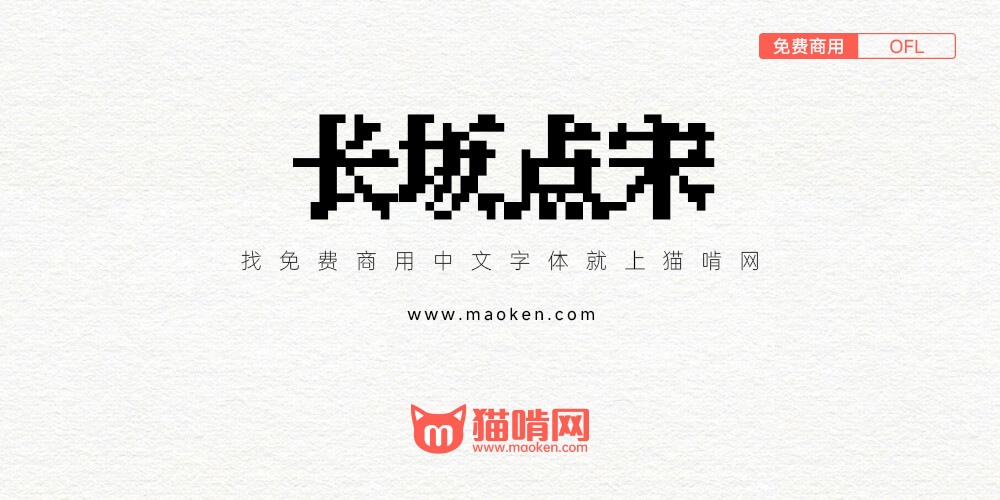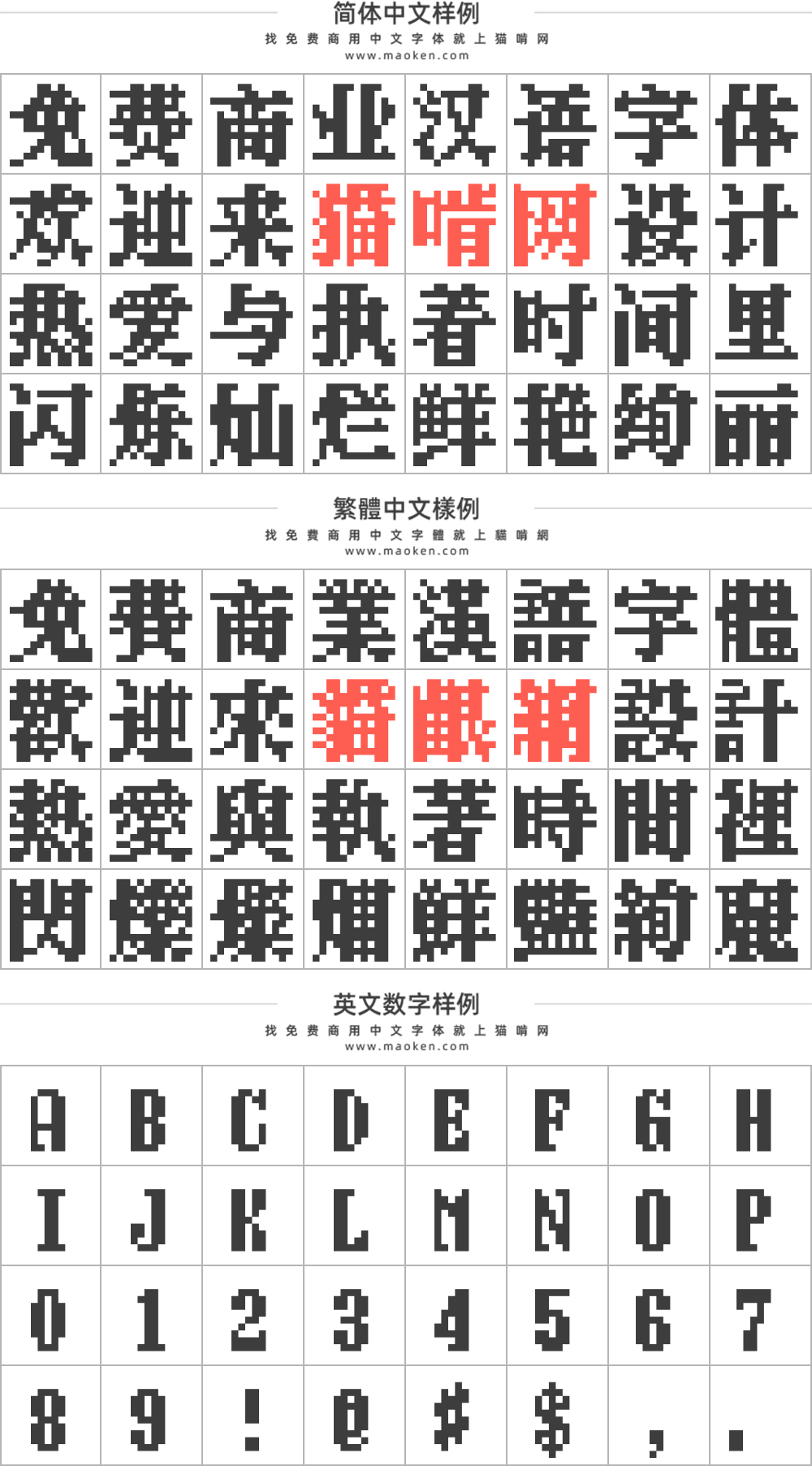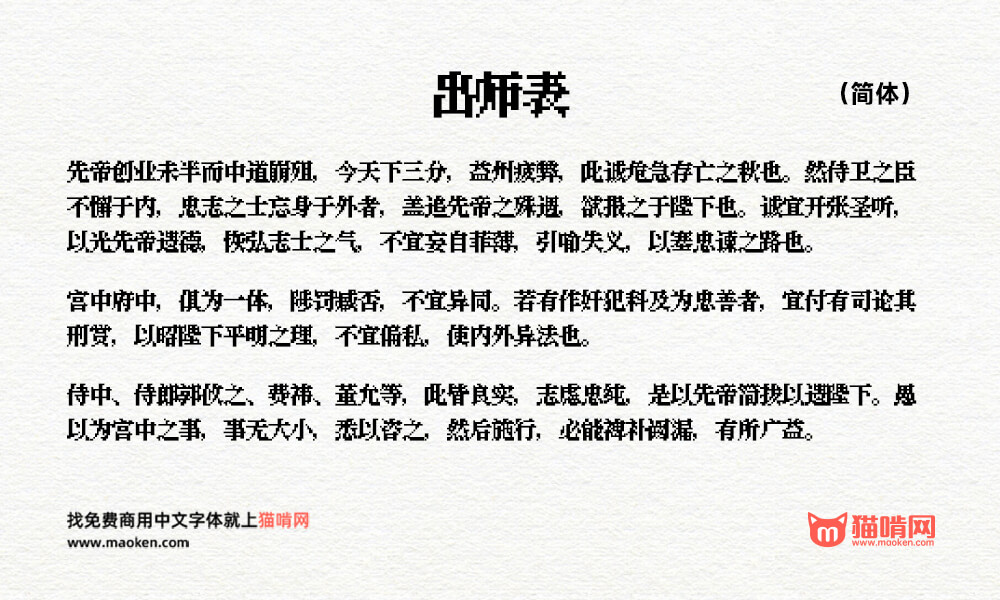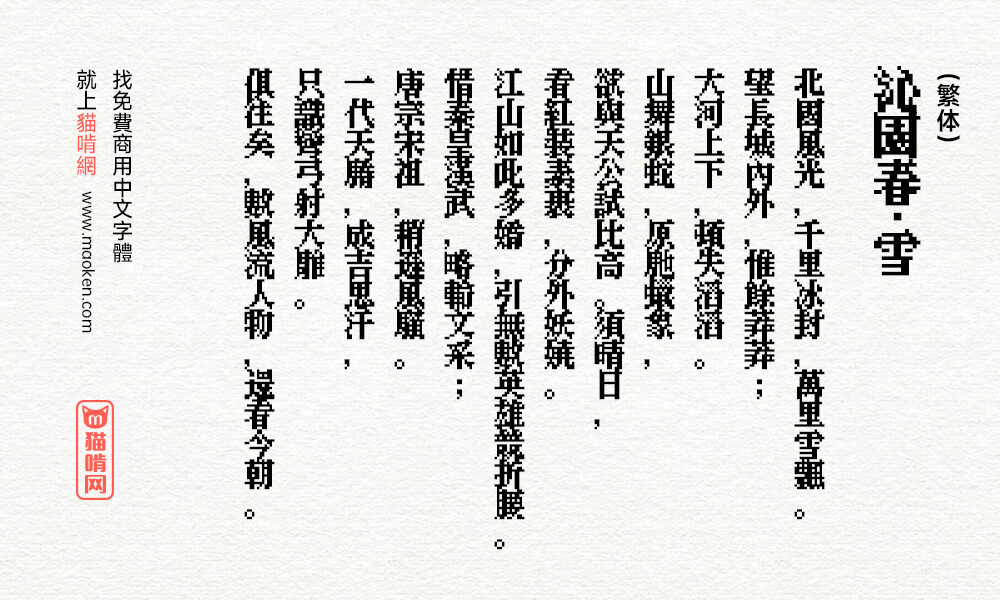
「长坂点宋 12」是基于 「KHドットフォントシリーズ」中的「KHドット道玄坂12」补足简体字和部分繁体字的 12px 点阵粗宋体,适合在复古风格的游戏和招牌中使用。
补全GB2312字符集中的所有汉字与部分常用繁体字,并调整部分汉字字形;补全汉语拼音与注音符号。
此外,部分竖画较多的汉字(如衄、嗣、騙)的处理方式和原字体也有所不同。
补全以下中文字符集:
- jf7000 当务字集基本包
修复以下字符的字形错误:
詵譸
追加竖排特性。
将全角句号、逗号和顿号右移1px以避免粘连。
- 修复原版字体遗留的无法被识别为等宽字体的问题
- 修复全角空格缺字的问题
- 增加部分符号与部分带音调符号的字母
- 补全以下中文字符集:
汉仪简繁字表
方正简繁字表
- 修复部分文字映射错误/宽度异常的问题
- 补全以下简体中文字符集:
通用规范汉字表哦
现代汉语通用字表 - 修复“梿”显示成“链”的问题
- 调整部分汉字的笔画处理方式
- 至此,简体字部分告一段落。(不出意外的话)
- 增加了484个汉字,其中包含《通用规范汉字表》中的所有二级字
- 重绘大多数“页”部、“马”部、“鸟”部的左右结构汉字
- 修复“蓯”“蓰”高度多出1px的问题
- 修复“礪”显示成“礰”的问题
- 补全以下繁体中文字符集: ※增补的汉字字形参考旧印刷体风格,不一定符合国标
GB/T 12345
常用國字標準字體表
Big5 常用汉字
常用字形表 - 补全元素周期表118个元素名称汉字
- 补全214个康熙部首 ※字形未与基本汉字作区分
- 调整部分汉字的笔画处理方式
- 修复部分汉字的字形错误
- 修复了竖排异常的问题。(感谢Luke036的帮助)
- 修复了部分标点符号宽度异常的问题。
- 补上了内嵌的bitmap font。
- 其他细节修改。
- 「长坂点宋 12」初版发布。
- 补全了GB2312字符集中的所有汉字与部分常用繁体字、补全了汉语拼音与注音符号、并调整了部分汉字字形。